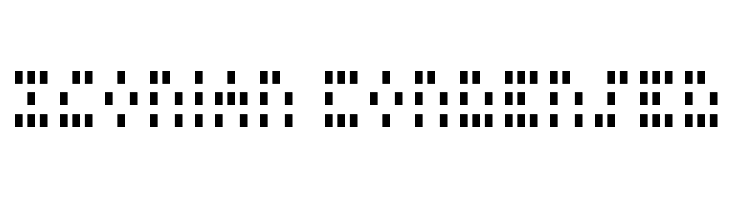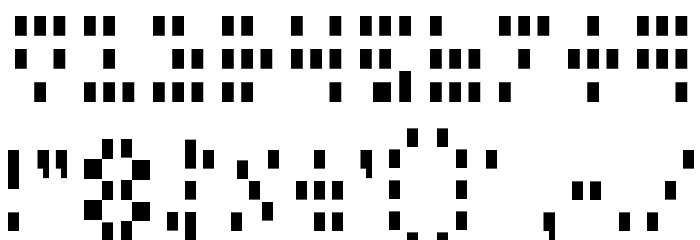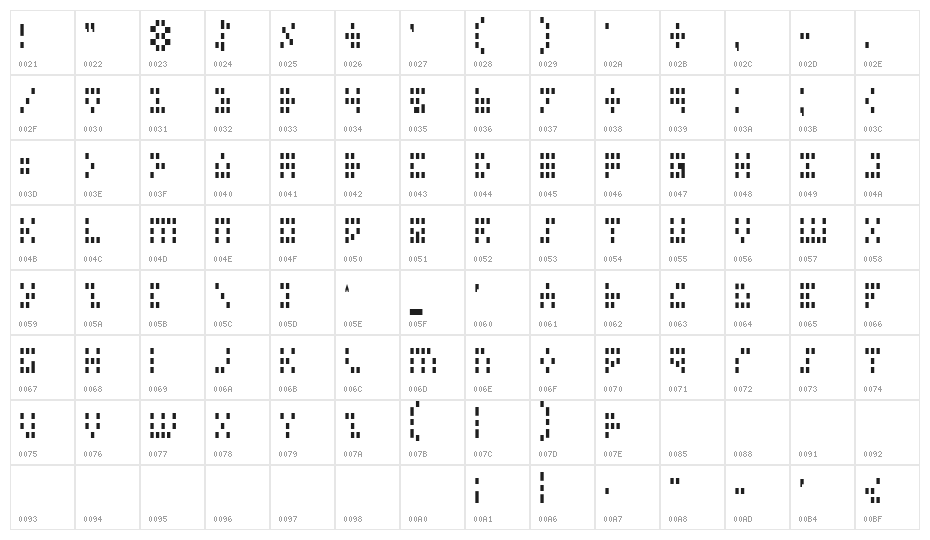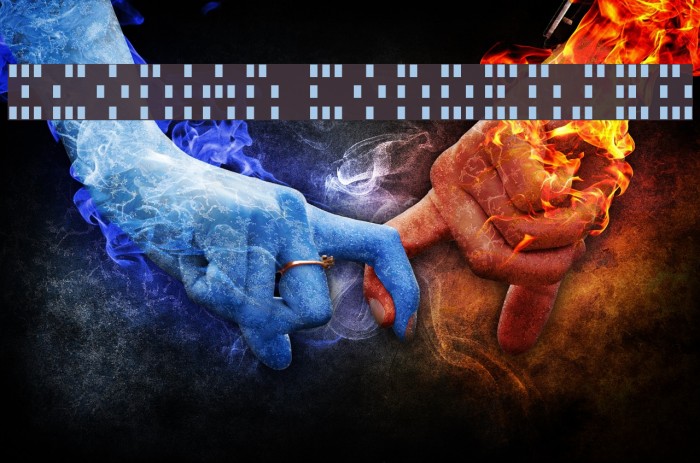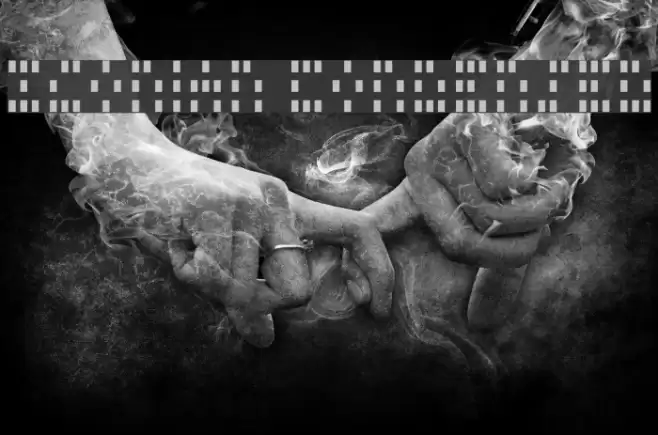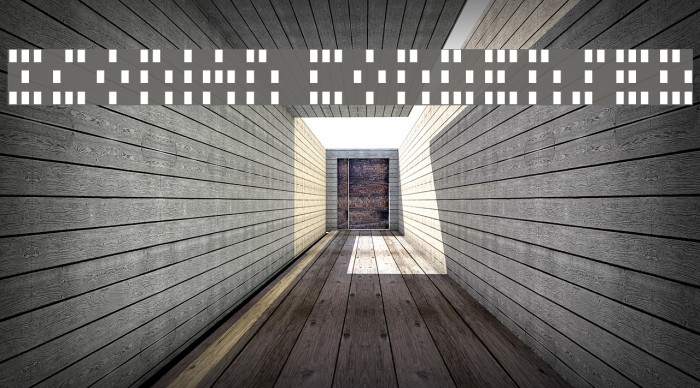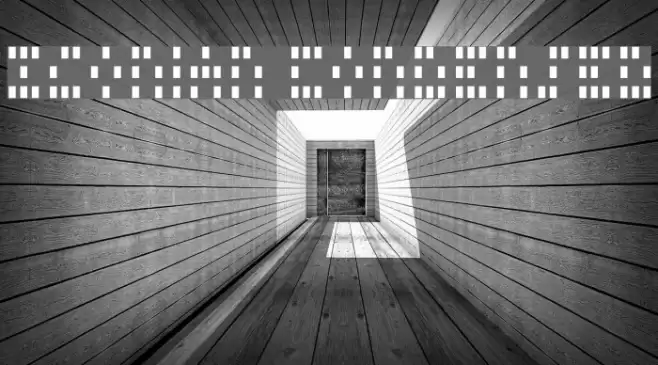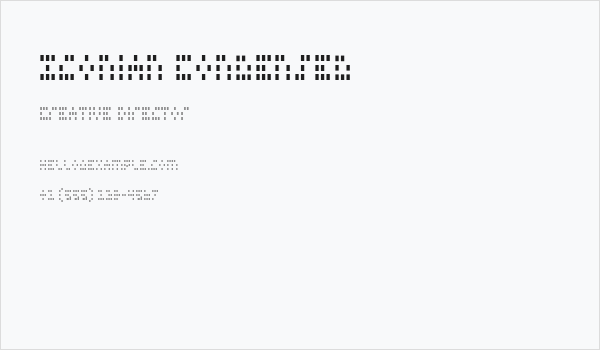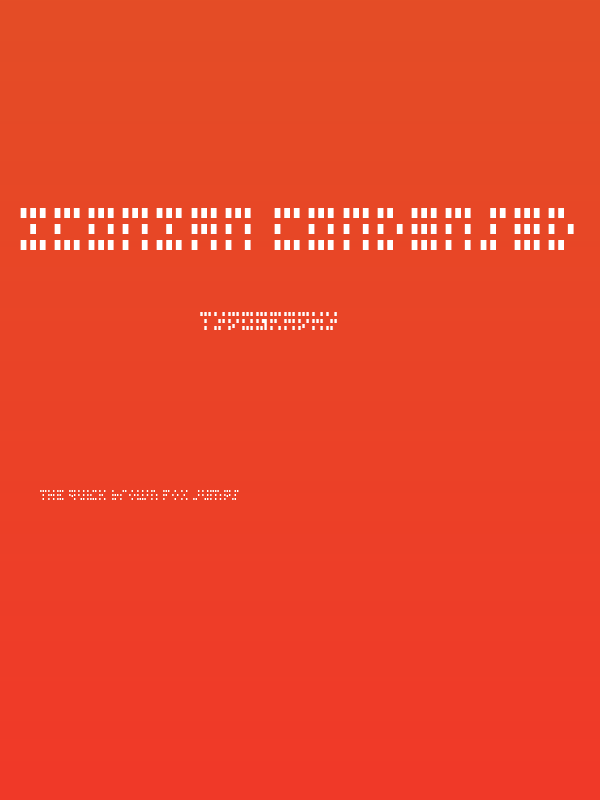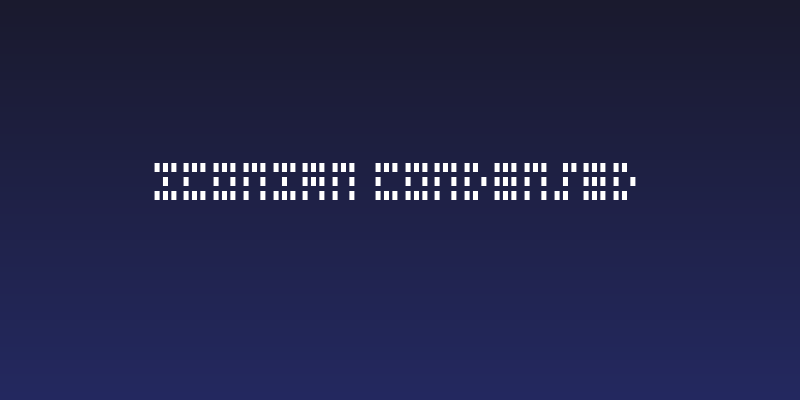
Iconian Condensed Font
| Proyectos propuestos | Ideal for video game graphics, tech-themed posters, digital art projects, or any design requiring a modern, digital aesthetic. |